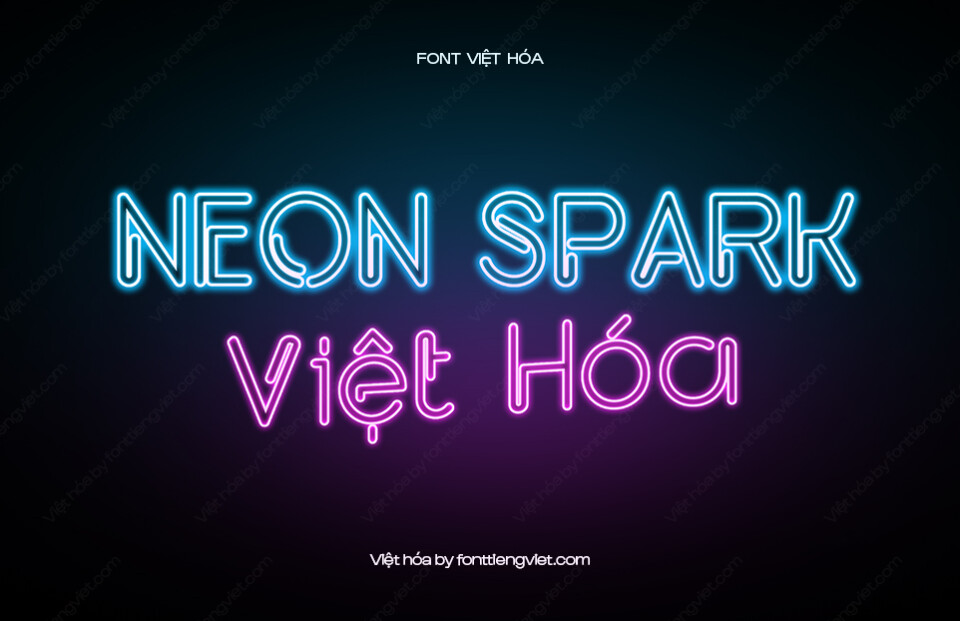
Giới thiệu về Font Việt hóa 1FTV VIP Neon Spark
Trong thế giới thiết kế đồ họa hiện nay, việc lựa chọn một bộ phông chữ phù hợp đóng vai trò quyết định đến tính thẩm mỹ của sản phẩm. Font Việt hóa 1FTV VIP Neon Spark là một lựa chọn tuyệt vời dành cho những ai đang tìm kiếm phong cách hiện đại và rực rỡ. Đây là bộ Font Chữ được tinh chỉnh kỹ lưỡng, hỗ trợ đầy đủ tiếng Việt giúp người dùng dễ dàng sử dụng trong các phần mềm thiết kế phổ biến mà không lo lỗi font.
Đặc điểm nổi bật của font chữ neon
Bộ phông này mô phỏng hoàn hảo hiệu ứng của các dải đèn neon phát sáng, mang lại cảm giác năng động và đậm chất công nghệ. Với các đường nét thanh mảnh nhưng chắc chắn, Font Việt hóa 1FTV VIP Neon Spark giúp các tiêu đề bài viết hoặc logo trở nên nổi bật hơn bao giờ hết trong không gian kỹ thuật số.
Ứng dụng thực tế của Font Việt hóa 1FTV VIP Neon Spark
Bộ font này cực kỳ phù hợp cho các bạn học sinh, sinh viên khi thực hiện các dự án sáng tạo tại trường học.
Thiết kế poster và bìa sách
Bạn có thể sử dụng font chữ này để làm nổi bật các thông điệp quan trọng trên poster sự kiện hoặc bìa tập san lớp. Sự độc đáo của nó giúp thu hút ánh nhìn ngay từ giây phút đầu tiên.
Sáng tạo nội dung trên mạng xã hội
Với xu hướng video ngắn và hình ảnh bắt mắt, việc áp dụng font neon sẽ giúp kênh cá nhân của bạn trông chuyên nghiệp và hiện đại hơn rất nhiều.